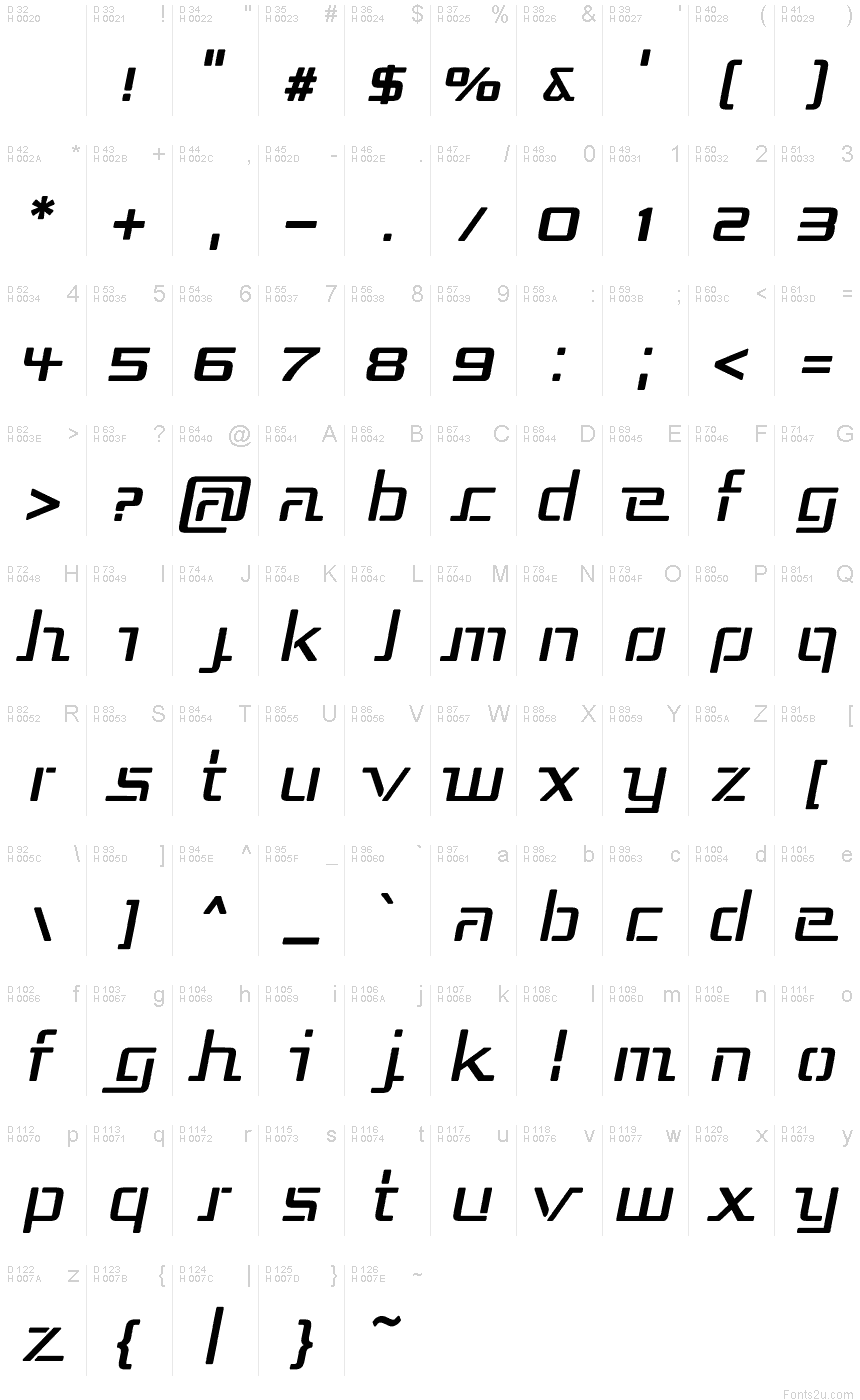
Republika III Italic
Republika III Italic di Apostrophe è un font display futuristico e gratuito, caratterizzato da un'inclinazione modulare rapida e da un'impronta decisamente techno. Le sue lettere sembrano scolpite in spesse barre arrotondate, che uniscono angoli squadrati a bordi morbidi; il risultato è un alfabeto fluido, compatto e leggermente robotico, ma mai freddo.
Questo font gratuito è la scelta ideale per poster di fantascienza, grafiche di musica elettronica, interfacce di gioco, titoli e packaging che ricercano un'estetica sintetica tipica del primo digitale. Funziona al meglio dove bastano poche parole a trasmettere lo stile – titoli brevi, loghi, copertine o tag di brand – poiché le sue forme inclinate e i contorni netti infondono dinamismo ancor prima di colore o impaginazione.